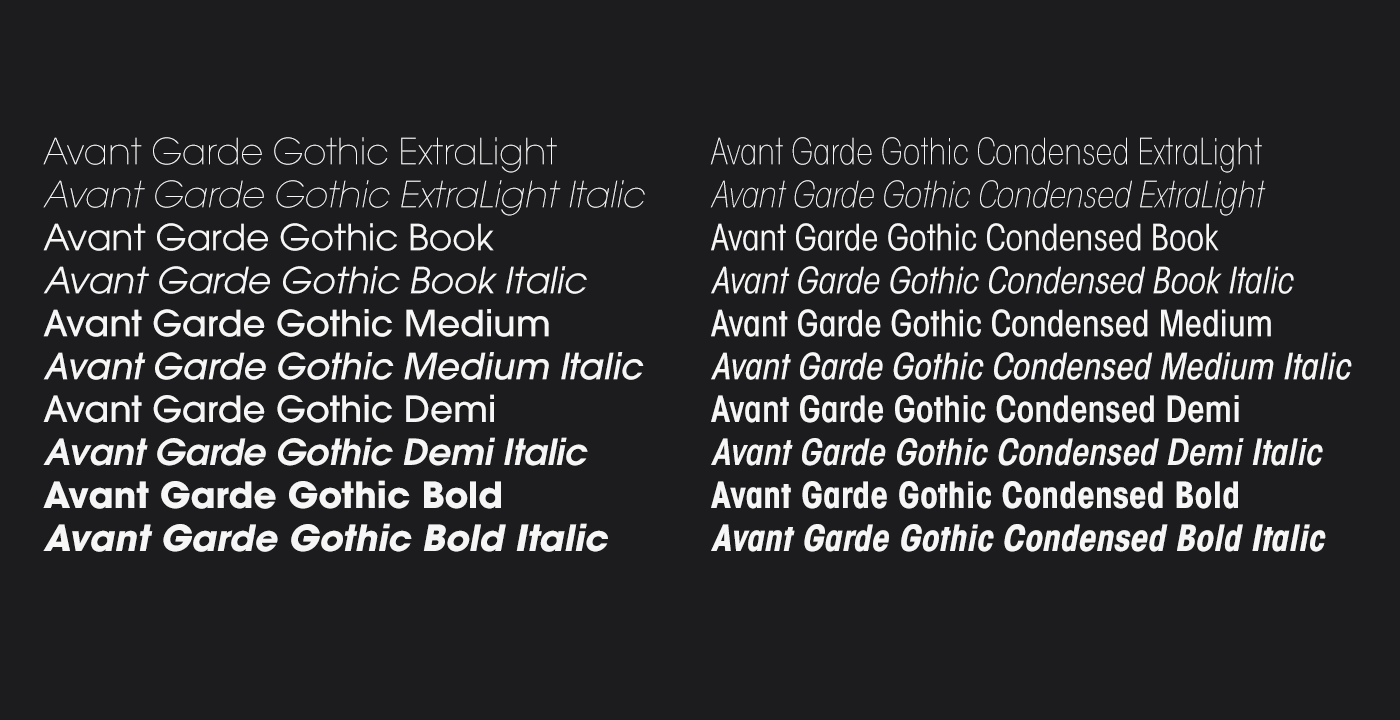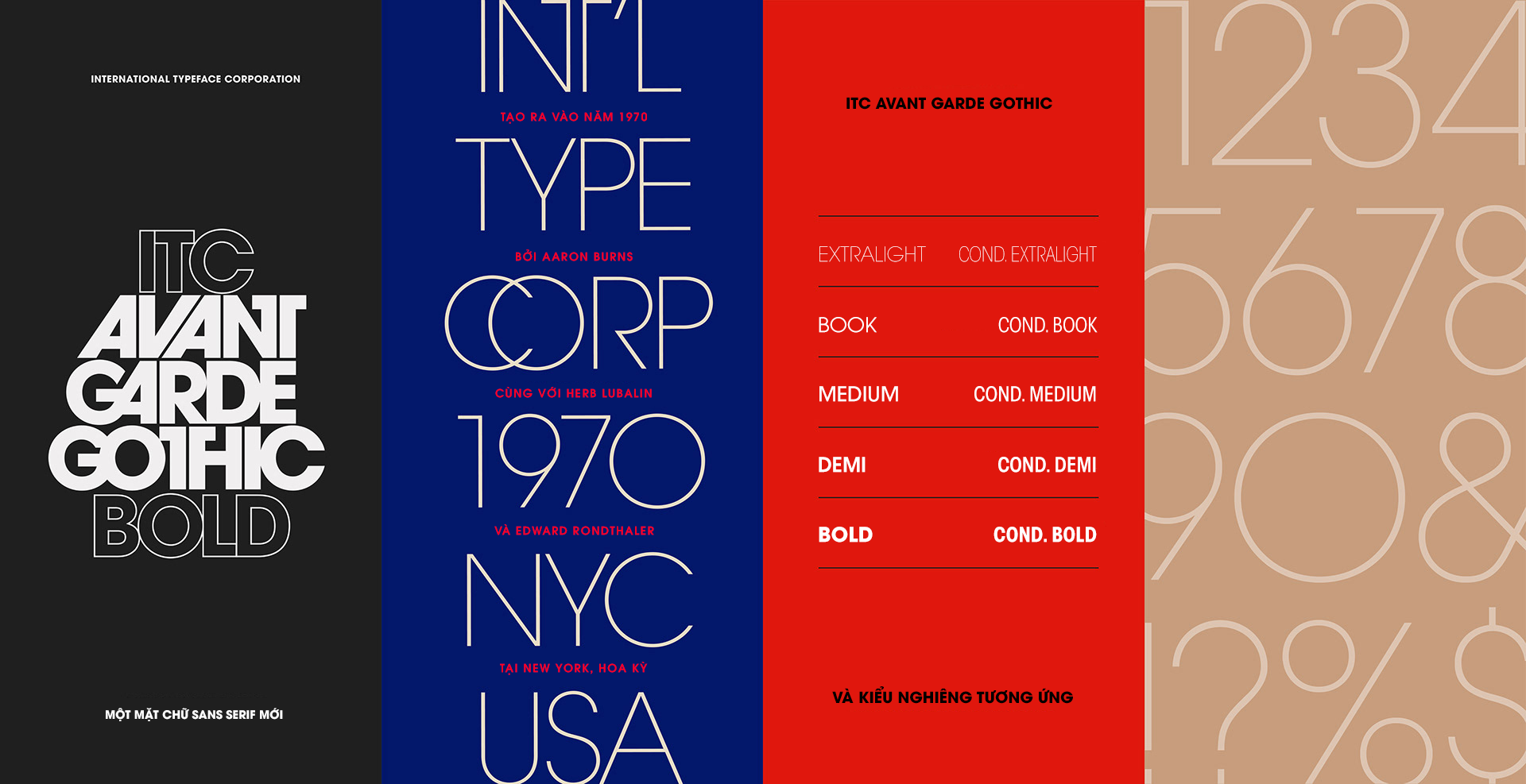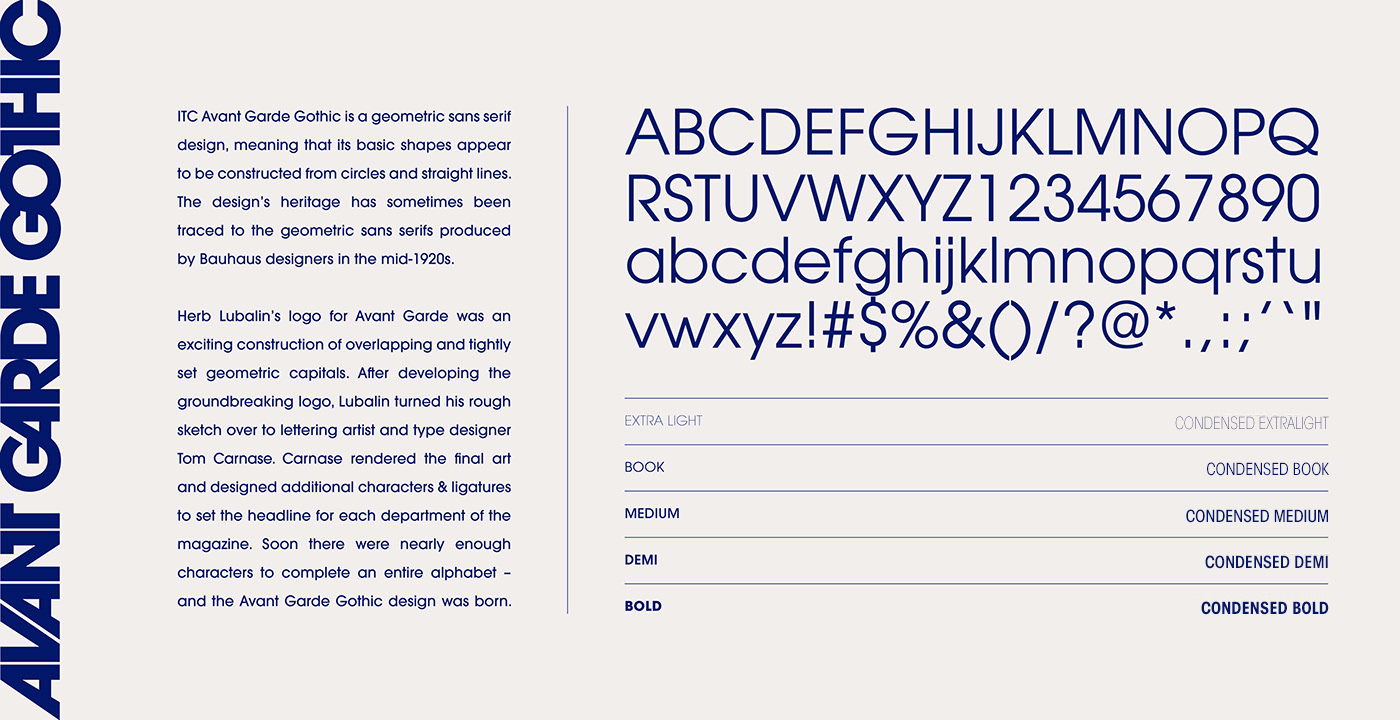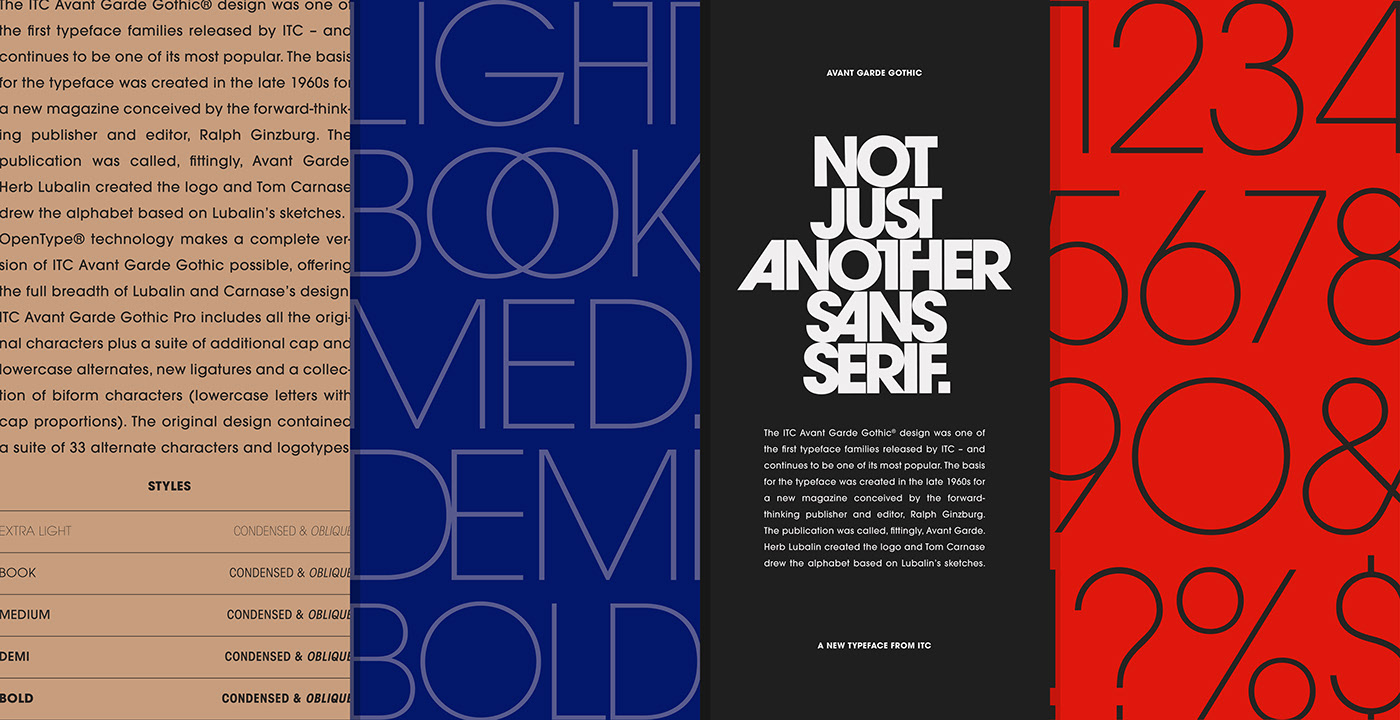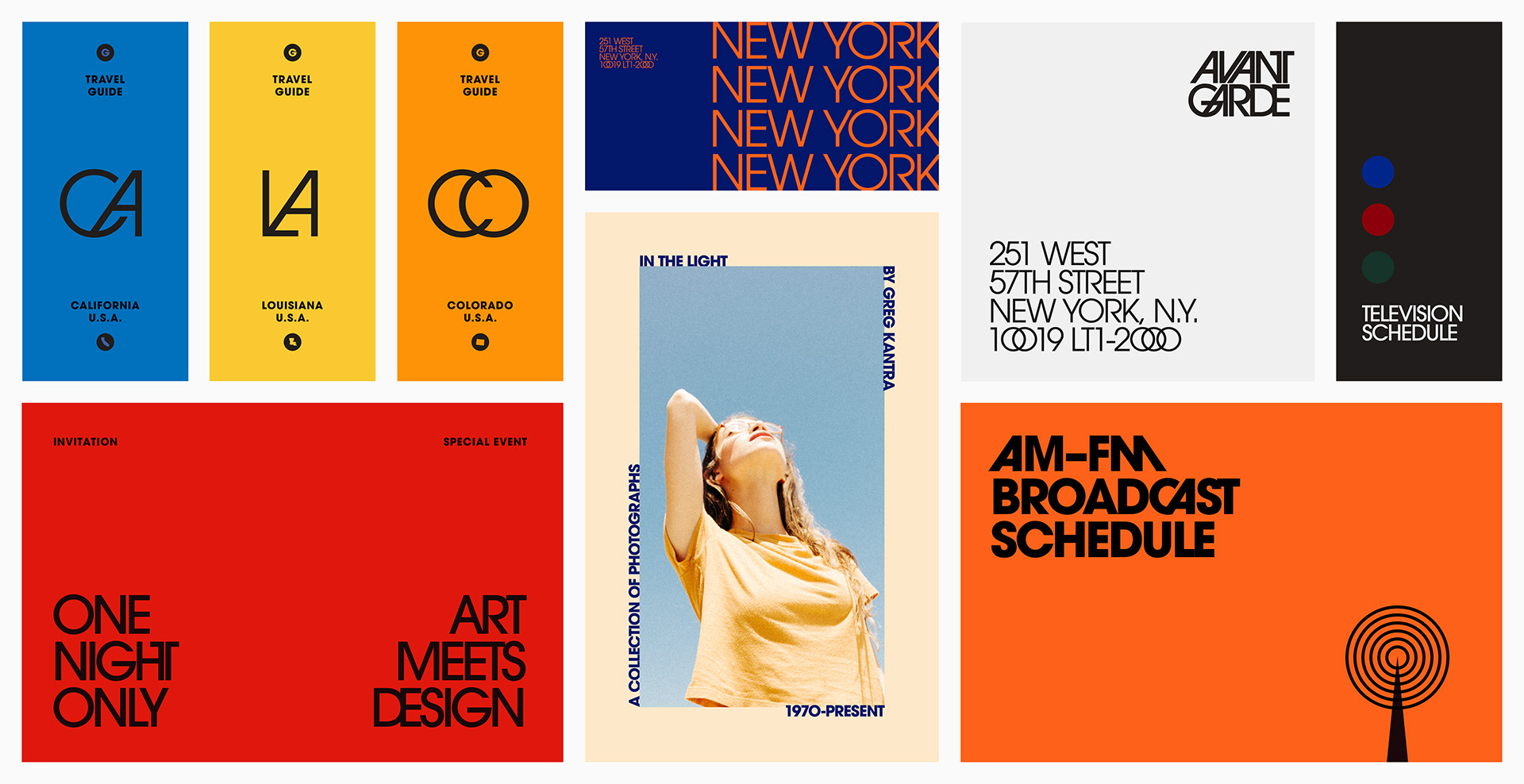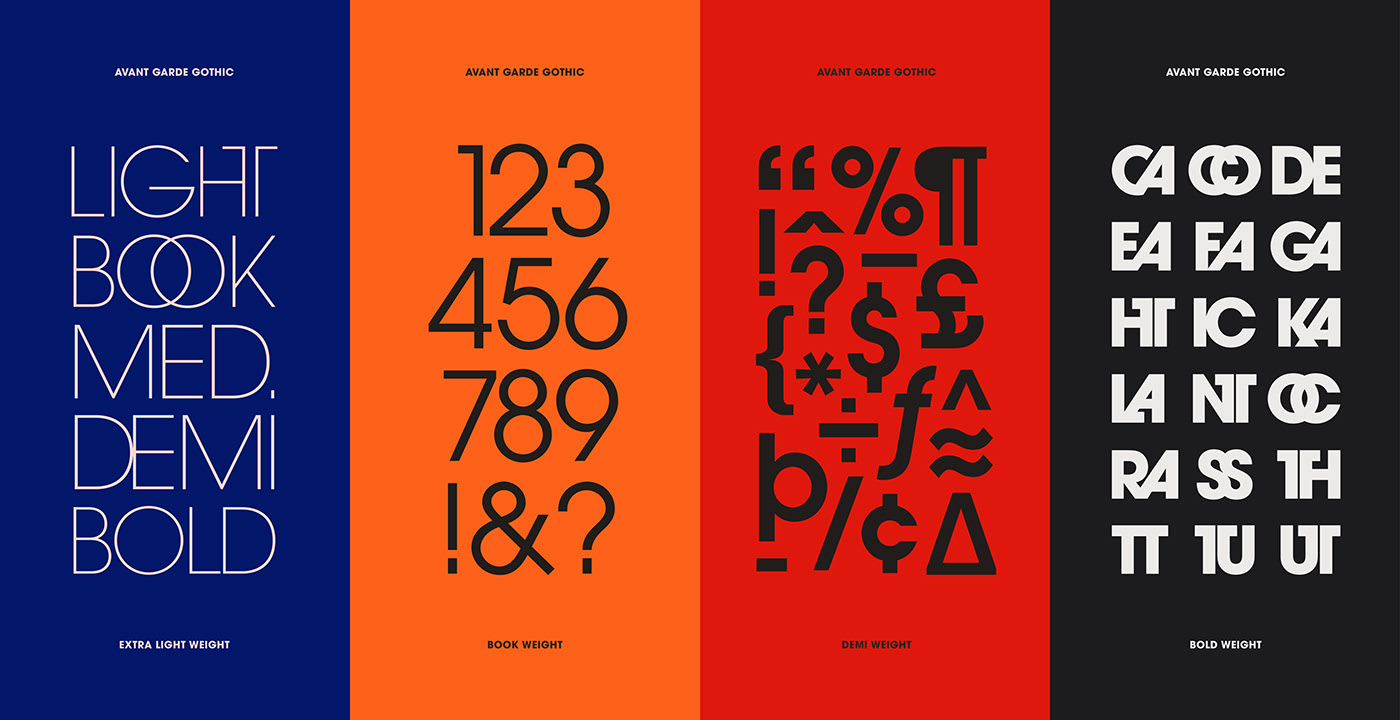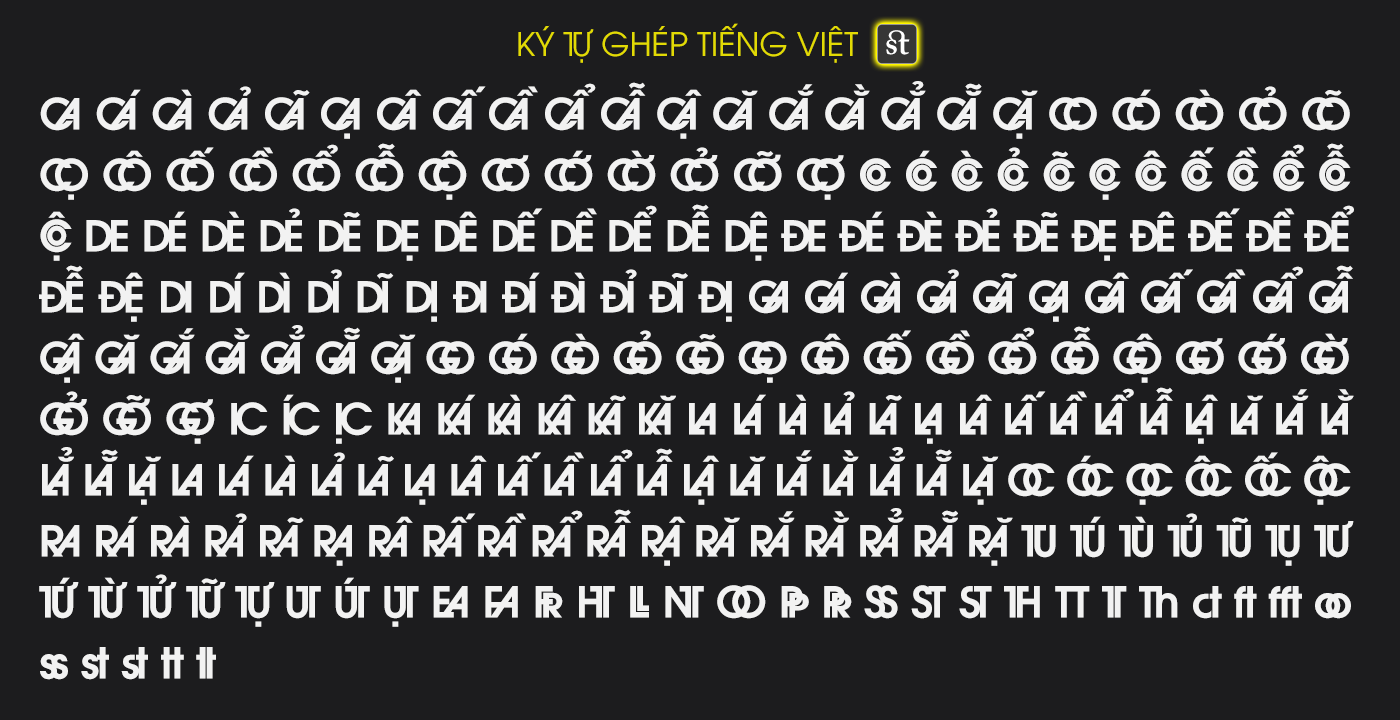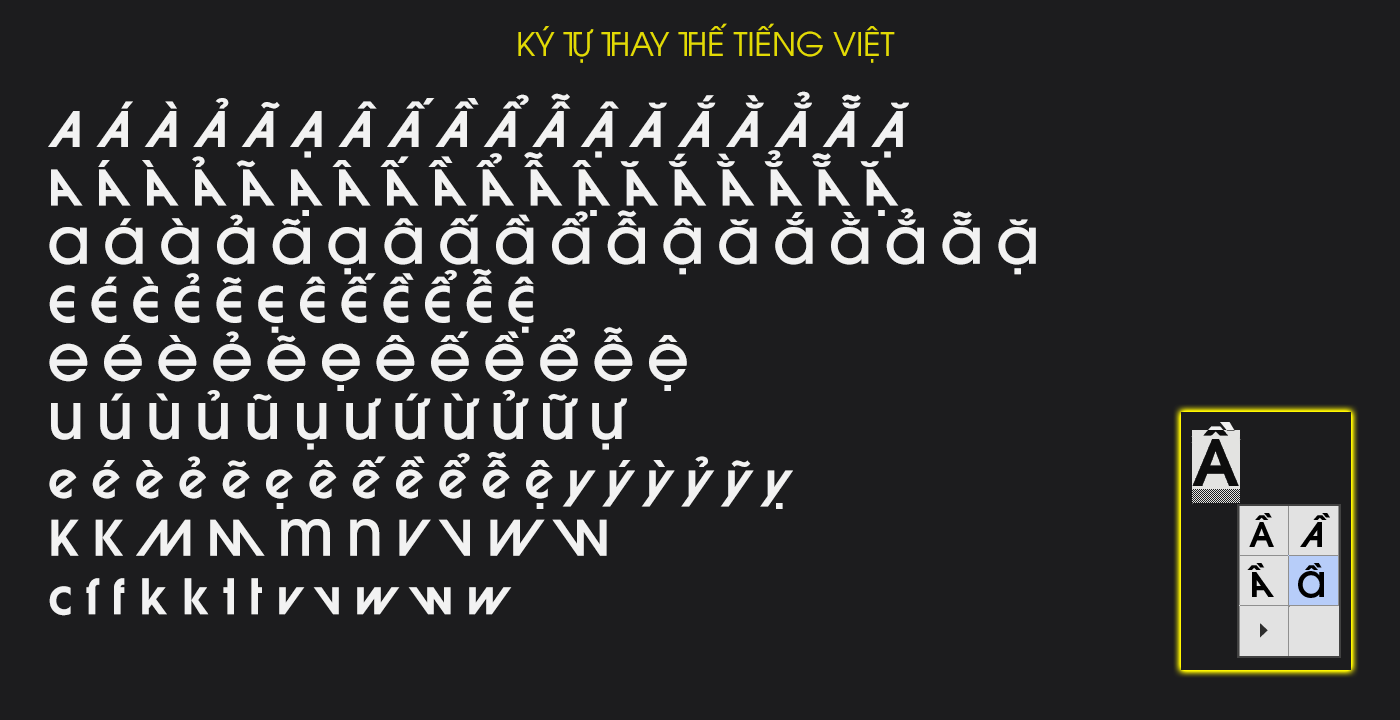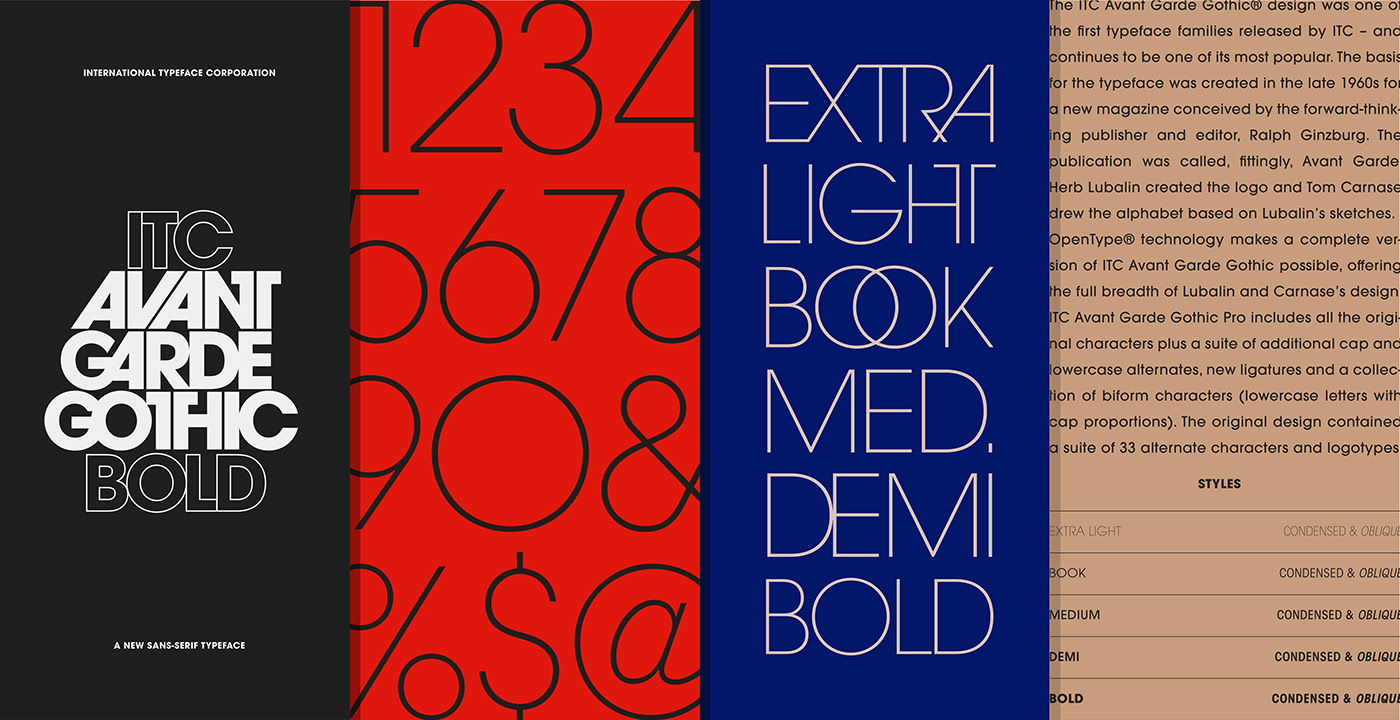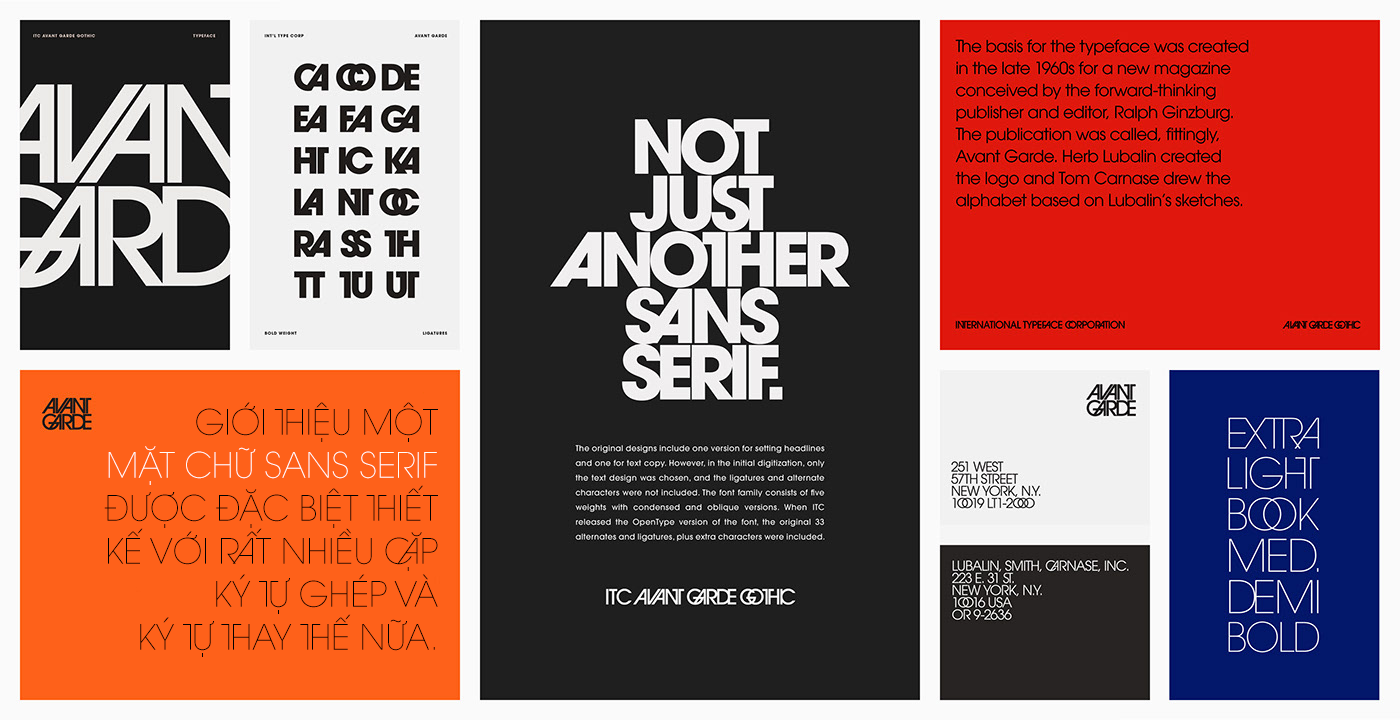
ITC Avant Garde Gothic là một bộ font dựa trên font logo được sử dụng trong tạp chí Avant Garde. Herb Lubalin đã tạo ra ý tưởng logo và kiểu chữ tiêu đề đi kèm. Sau đó, ông và Tom Carnase, một đối tác trong công ty thiết kế của Lubalin, đã cùng nhau biến ý tưởng đó thành một kiểu chữ hoàn chỉnh. Các font condensed (thu hẹp) được Ed Benguiat thiết kế vào năm 1974, và các font oblique (nghiêng) được André Gürtler, Erich Gschwind và Christian Mengelt thiết kế vào năm 1977. Các thiết kế gốc bao gồm một phiên bản dùng cho tiêu đề và một phiên bản cho nội dung văn bản. Tuy nhiên, trong quá trình số hóa ban đầu, chỉ có thiết kế dành cho văn bản được chọn, và các nối chữ (ligatures) cùng ký tự thay thế (alternate characters) không được bao gồm. Bộ font này bao gồm 5 độ dày (4 cho condensed), với các kiểu nghiêng bổ sung cho các font có độ rộng lớn nhất. Khi ITC phát hành phiên bản OpenType của font này, 33 ký tự thay thế và nối chữ gốc, cùng với các ký tự bổ sung, đã được đưa vào.
Nhà thiết kế: Edward Benguiat, André Gürtler, Herb Lubalin, Tom Carnase, Erich Gschwind, Christian Mengelt
Nhà phát hành: ITC